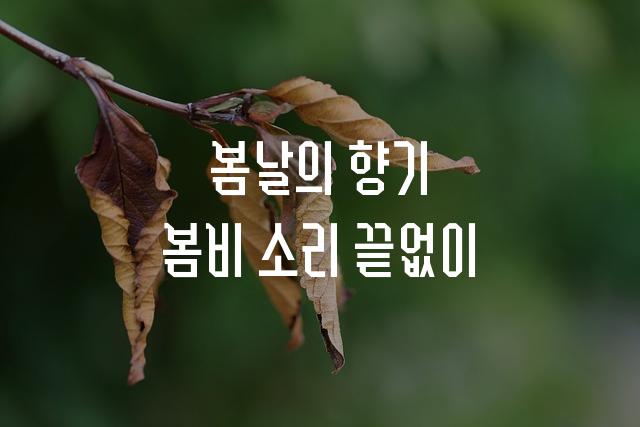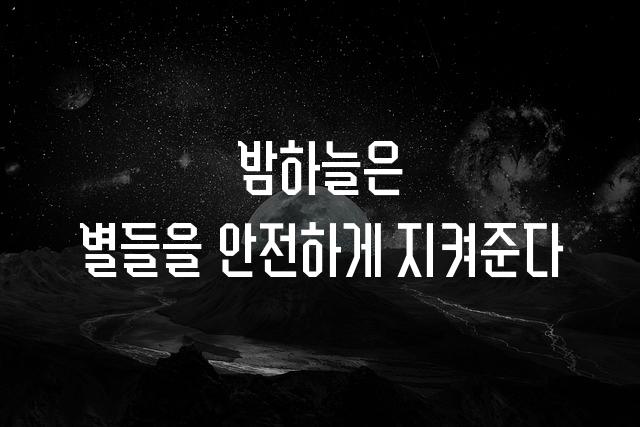
사월십육일체 약속은 4・16재단에서 제작한 독특하고 키가 큰 장식체 폰트입니다. 이 폰트는 현대적 감성과 도전적인 디자인을 결합해 창의적인 표현의 폭을 넓혀줍니다.
사월십육일체 약속은(는)
두꺼운 스타일, 장식 스타일, 별모양/패턴, 길고/크고 계열의 생김새를 가지고 있으며
포스터, 초대장, 일기/편지 등에서 자주 활용되며, 효과적인 메시지 전달에 적합합니다.
이 폰트는 문화/예술, 이벤트/웨딩, 관광/여행 분야에 잘 어울리며,
감성적인, 편안한, 예술적인 느낌을 담고 있는 것이 특징입니다.